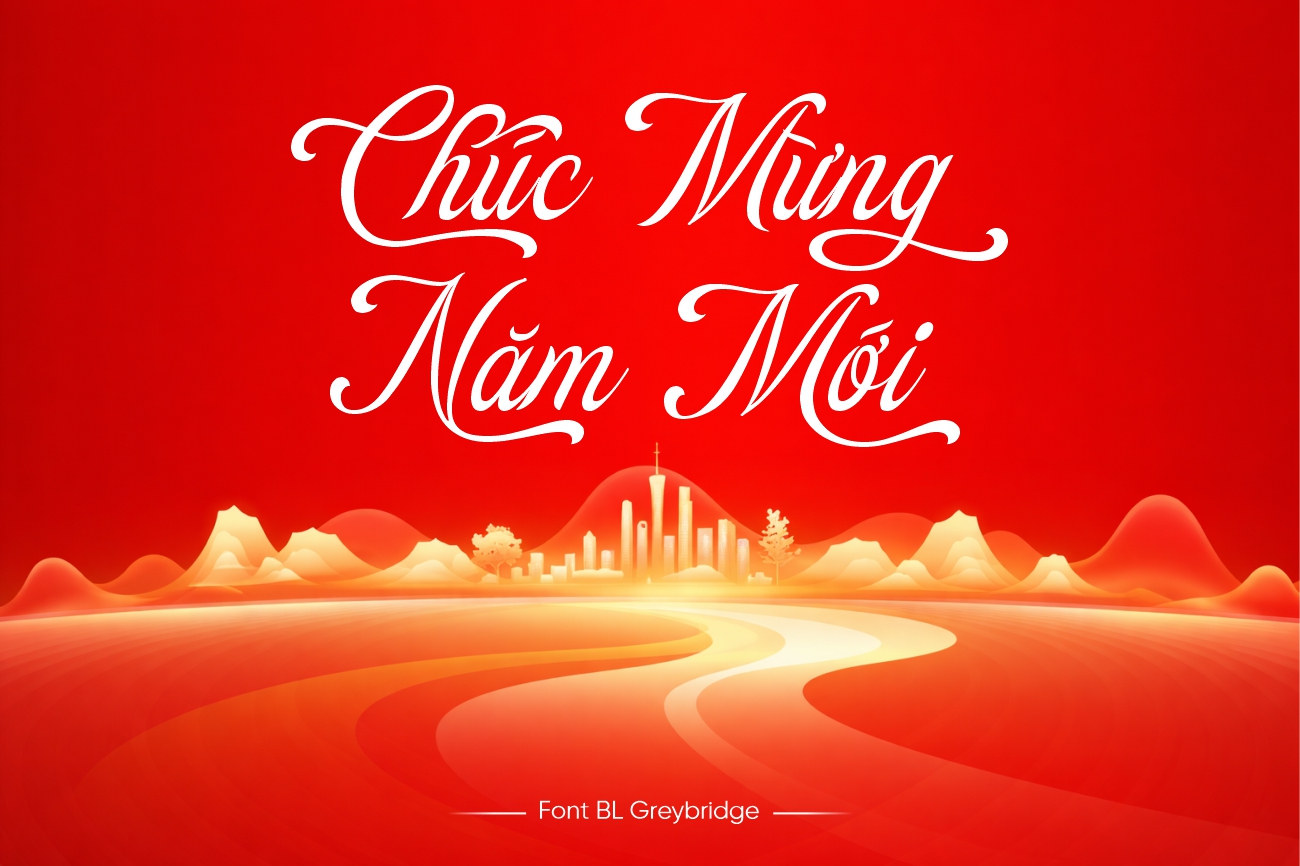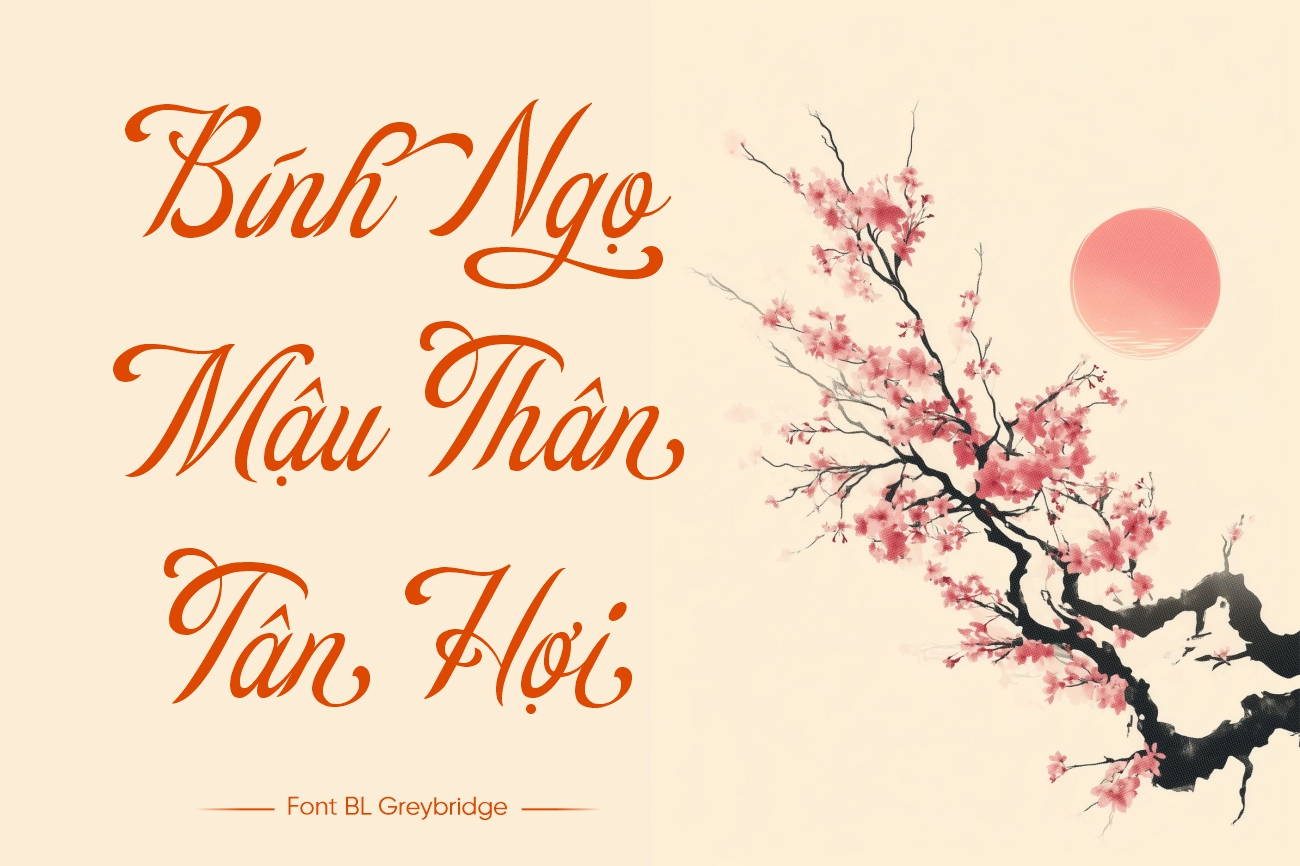
BL Greybridge - Phông chữ Calligraphy cổ điển
Tác giả Letterhend Studio
Việt hóa Font BL
BL Greybridge là phiên bản Việt hóa của font chữ Greybridge do Letterhend Studio thiết kế, được Team BL chuyển ngữ và tinh chỉnh để đáp ứng đầy đủ nhu cầu sử dụng tiếng Việt. Nguyên bản Greybridge mang tinh thần cổ điển pha hiện đại, hướng đến sự sang trọng và cảm xúc thị giác tinh tế. Sau quá trình Việt hóa, BL Greybridge không chỉ giữ được cá tính thẩm mỹ vốn có mà còn đảm bảo hệ thống dấu tiếng Việt rõ ràng, cân đối, giúp font hoạt động ổn định trong nhiều bối cảnh thiết kế khác nhau, từ in ấn truyền thống đến truyền thông hiện đại.
Về kiểu dáng, BL Greybridge sở hữu nét chữ mềm mại nhưng có trọng lượng rõ ràng, tạo cảm giác chỉn chu và cao cấp ngay từ cái nhìn đầu tiên. Các đường cong được xử lý mượt mà, kết hợp cùng trục nét vững chắc giúp chữ vừa duyên dáng vừa dễ đọc. Chính sự hài hòa này khiến font đặc biệt phù hợp cho các thiết kế mang tính cảm xúc và trang trọng như font chữ thiệp cưới, thiệp báo hỷ hay thiệp mời sự kiện. Khi sử dụng trong bố cục tổng thể, BL Greybridge mang lại cảm giác tinh tế, không phô trương nhưng vẫn đủ nổi bật để tạo dấu ấn thị giác.
Không chỉ giới hạn trong lĩnh vực cưới hỏi, BL Greybridge còn được ứng dụng hiệu quả trong quảng cáo, nhãn mác, logo và các ấn phẩm truyền thông cao cấp. Nét chữ vừa có chiều sâu cổ điển, vừa mang hơi thở hiện đại giúp font thích nghi tốt với nhiều phong cách thương hiệu khác nhau. Khi sử dụng cho thiết kế logo hoặc bao bì, BL Greybridge tạo cảm giác tin cậy, lịch sự và có giá trị lâu dài. Đối với các ấn phẩm như tạp chí, font giúp nội dung trở nên cuốn hút hơn mà vẫn giữ được sự trang nhã cần thiết cho bố cục nhiều chữ.
Xét về nguồn gốc, Greybridge phản ánh rõ phong cách thiết kế đặc trưng của Letterhend Studio, nơi luôn đề cao sự tinh xảo và cảm xúc trong từng ký tự. Qua bàn tay Việt hóa của Team BL, font được điều chỉnh kỹ lưỡng về khoảng cách, tỷ lệ và dấu tiếng Việt để đảm bảo tính thẩm mỹ lẫn khả năng ứng dụng thực tế. Nhờ đó, BL Greybridge trở thành lựa chọn linh hoạt cho font chữ thiệp cưới, thiệp mời, quảng cáo, logo hay tạp chí, đáp ứng tốt cả nhu cầu trang trí lẫn truyền tải nội dung một cách rõ ràng, sang trọng và chuyên nghiệp.